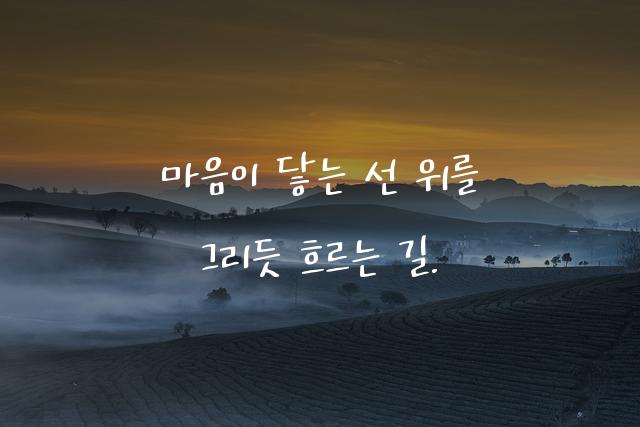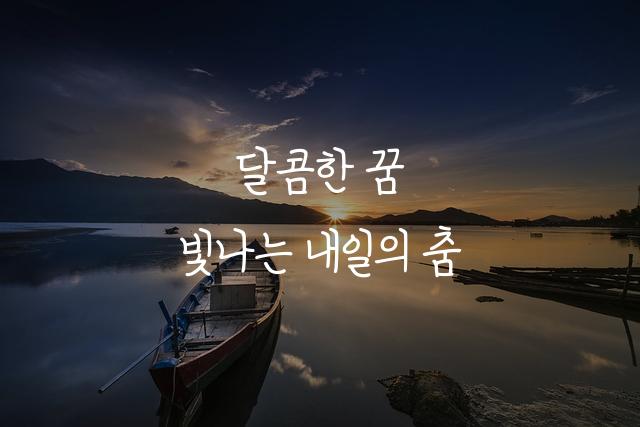
이서윤체
이서윤체는 흥국생명에서 제작한 폰트로, 아이들의 손글씨에서 영감을 받아 귀엽고 또박또박한 느낌을 잘 살려냈습니다. 이 폰트는 따뜻한 감성을 전달하며, 친근감을 주는 디자인이 특징입니다.
흥국생명
1가지 굵기
한국어, 영어, 일본어, 특수문자 지원
이서윤체의 목소리는 마치 행복한 아이가 들려주는 이야기처럼 따뜻하고 경쾌합니다.
이서윤체은(는) 손글씨, 귀여운 스타일, 레트로, 감성적인 계열의 생김새를 가지고 있으며
포스터, 일기/편지 등에서 자주 활용되며, 효과적인 메시지 전달에 적합합니다.
이 폰트는 문화/예술, 이벤트/웨딩 분야에 잘 어울리며,
감성적인, 예술적인 느낌을 담고 있는 것이 특징입니다.